ペン1本ですぐにマネできる!ねこねこさんのハンドレタリング2
インプレスグループでデザイン分野のメディア事業を手がけるエムディエヌコーポレーションは、ねこねこ氏著書による、ハンドレタリングの楽しさが詰まった一冊「ペン1本ですぐにマネできる!ねこねこさんのハンドレタリング2」を発売した。
「ペン1本ですぐにマネできる!ねこねこさんのハンドレタリング2」では、手帳やノートに使える、アルファベット、ひらがな、カタカナの書体はもちろん、数字や記号の書き方もお手本と共に紹介している。
書き方のポイントや上手に書くコツなどもわかりやすく解説。
また、ハンドレタリングのアクセントとして使える飾りやイラスト、曜日や日付、お祝いのフレーズなども収録しているので、飾りや文字の組み合わせを変えて楽しむことができる。
さらに、「ペン1本ですぐにマネできる!ねこねこさんのハンドレタリング2」で紹介した文字やイラストを使用した実例も参考になる。
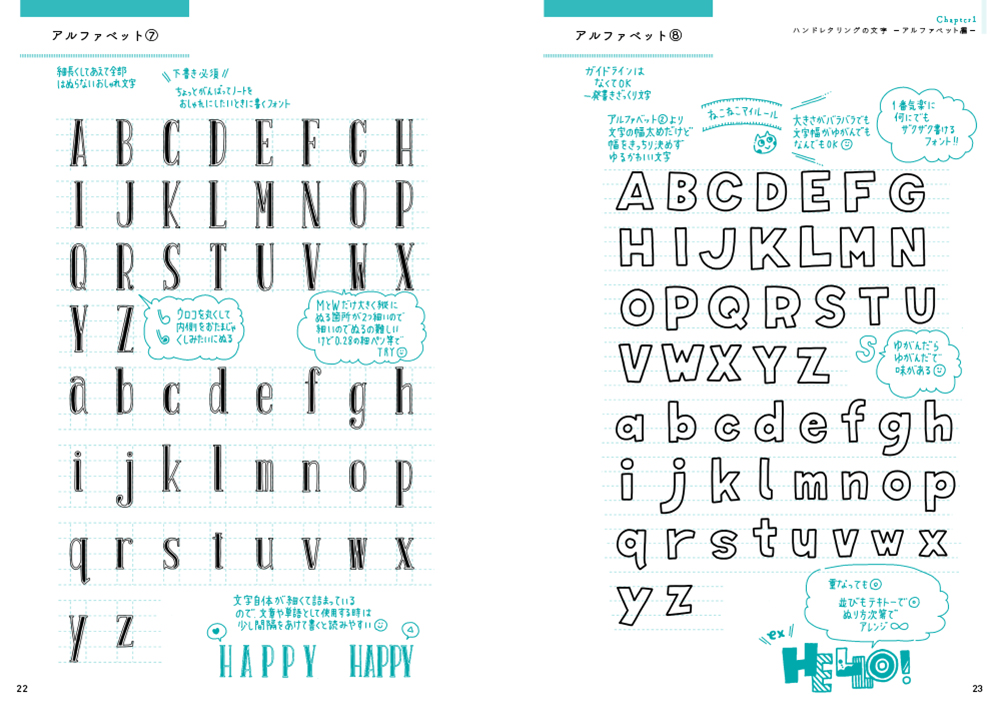
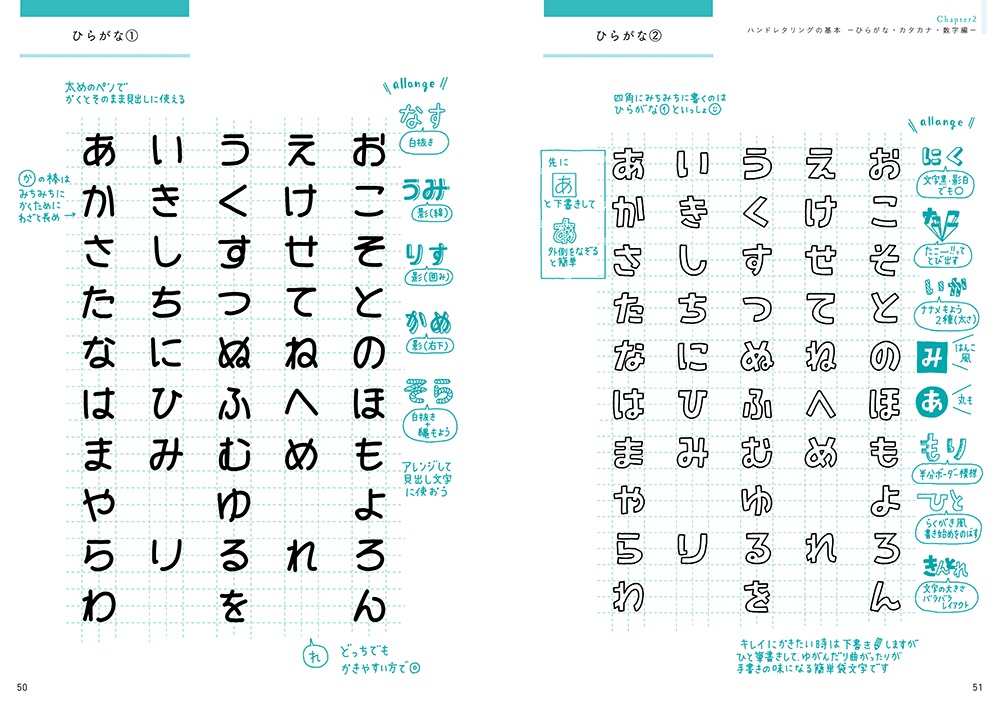
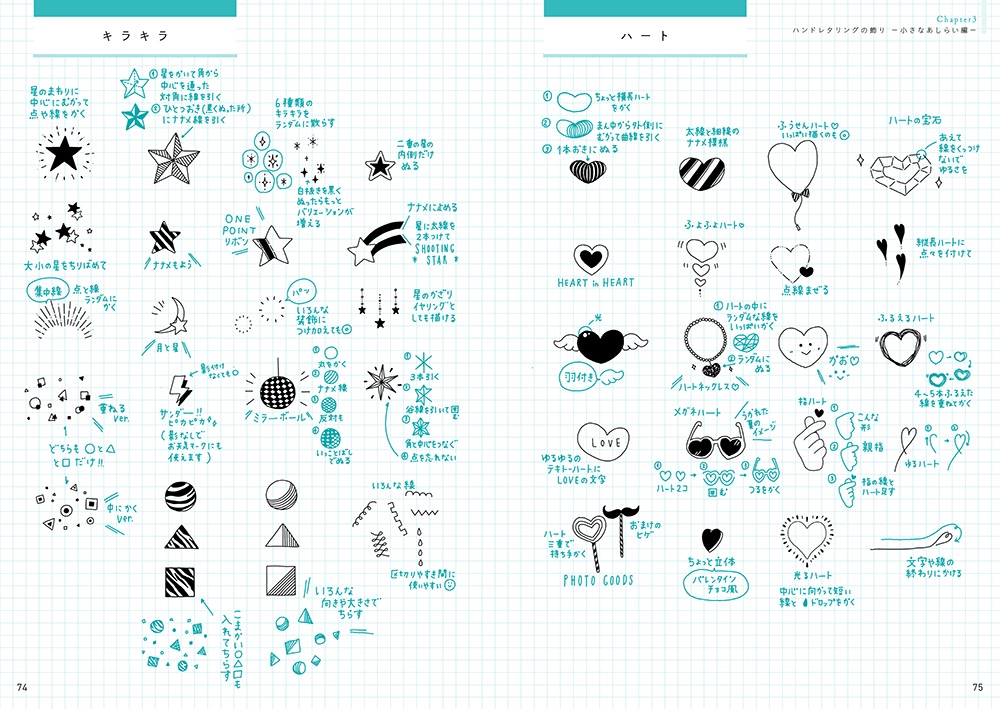
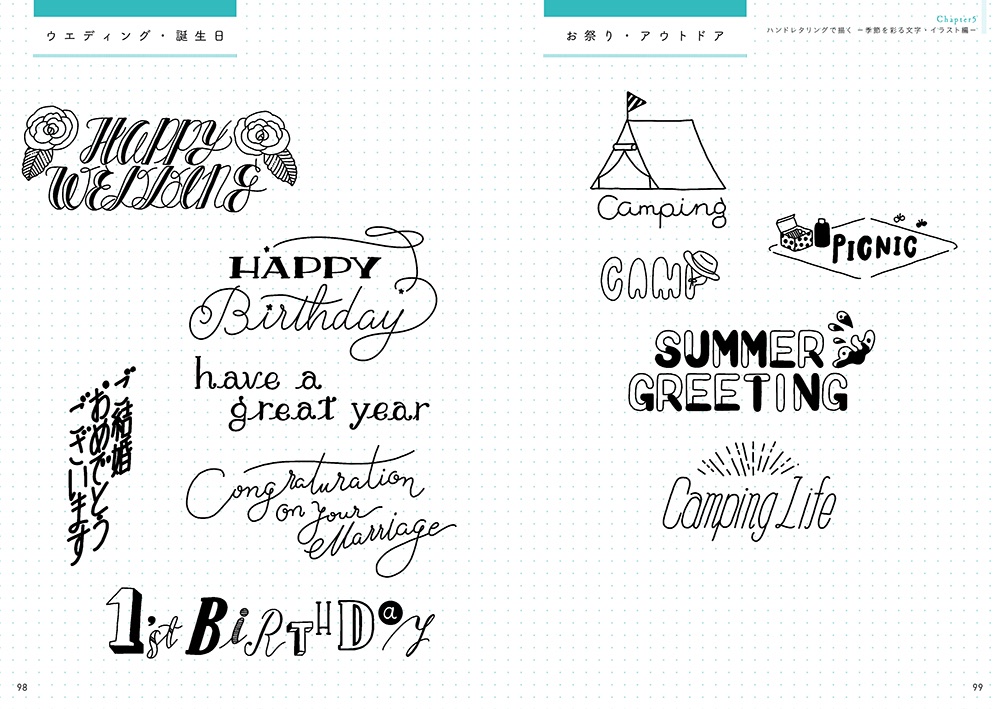
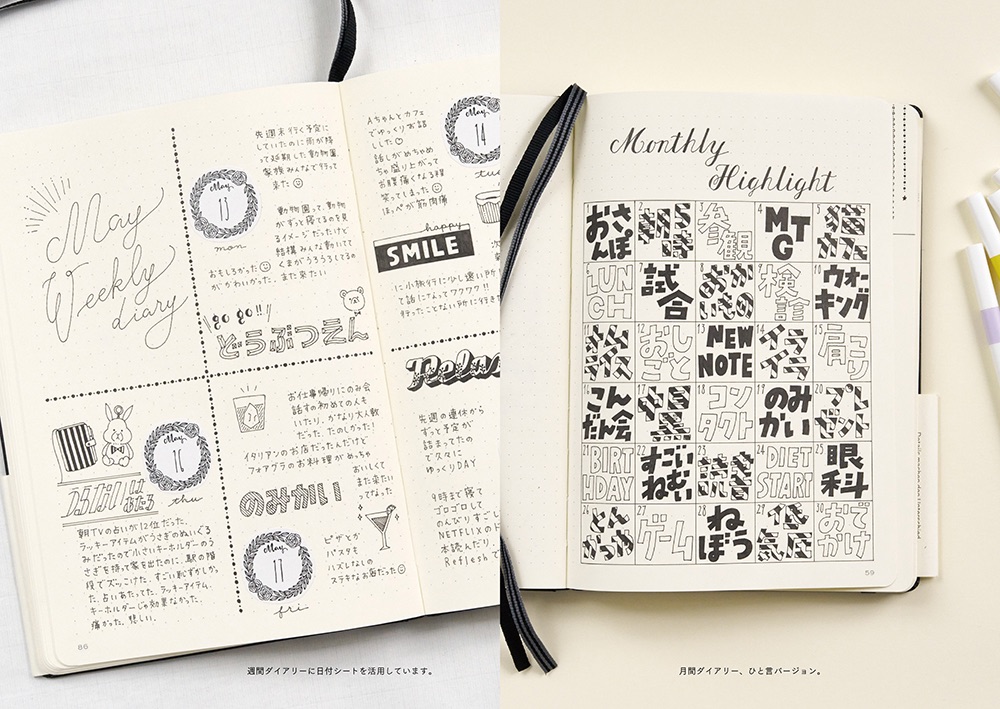
「ペン1本ですぐにマネできる!ねこねこさんのハンドレタリング2」の特長
・ハンドレタリングの初心者でも取り組みやすい
・ねこねこさんのシンプルでかわいらしいスタイル
・なぞり書き練習ページの特典付き
・シンプルな道具での表現
・前作の続編として、ファンにとって待望の一冊